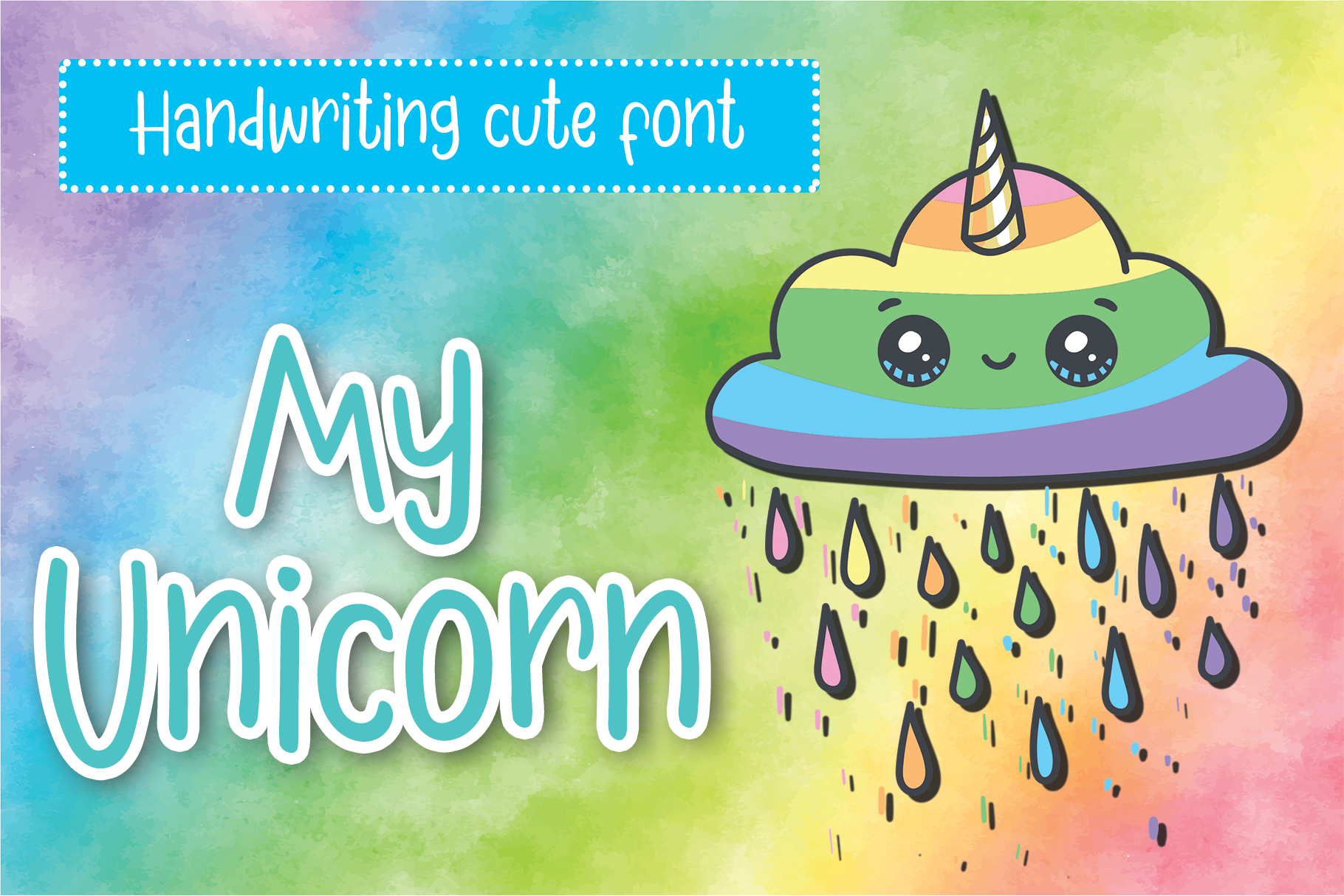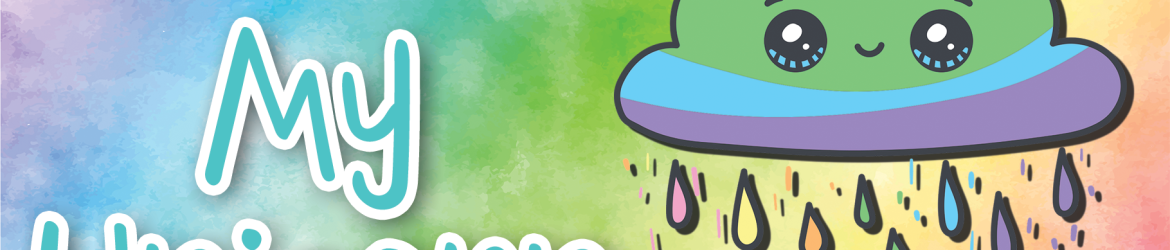
My Unicorn Font – Download Grátis
A fonte ‘My Unicorn Font’ é uma elegante letra feita especialmente para criar ideias criativas em estilo desenho animado. Inspirada no unicórnio mágico, esta font foi projetada com um toque de encanto para aqueles buscando adicionar um pouco mais de magia à sua arte digital. Seja para personalizar posts na Instagram ou até mesmo para DIY projetos decorativos, ela transformará qualquer ideia criativa em uma verdadeira obra de arte. Ideal tanto para designers digitais quanto para quem deseja dar um toque especial a seus trabalhos manuais, esta font é perfeita para aqueles que valorizam um toque único e mágico nas suas criações.